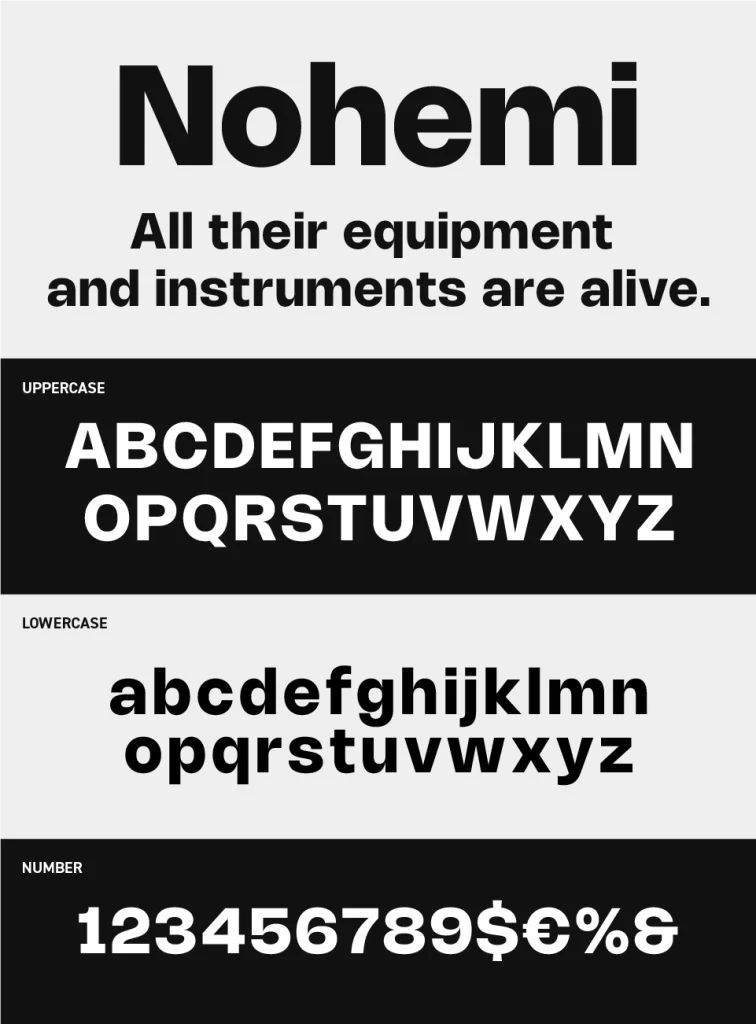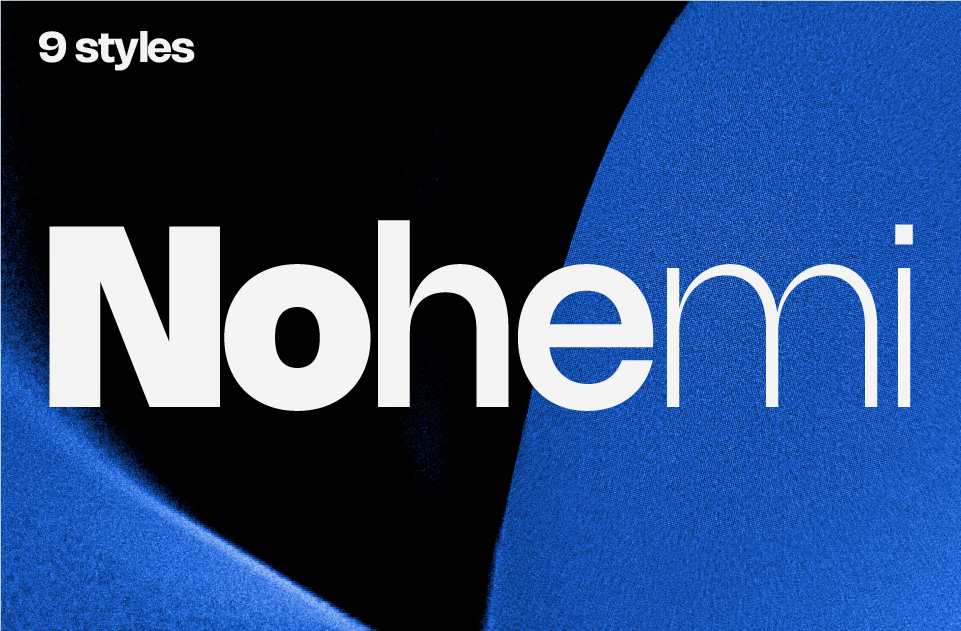
Nohemi Font
Nohemiは、丸みを抑えた幾何学的なシルエットと、均整の取れた力強いストロークが特徴のモダンサンセリフフォントです。
無駄を削ぎ落としたシンプルなデザインながら、一文字ごとのプロポーションが美しく整えられており、洗練された都会的な印象を与えます。太めのウェイトでも重たくなりすぎず、スマートさを保っているのも魅力です。
ブランディングやWebデザイン、アプリ、広告、企業ロゴなど、幅広いデザインシーンで活躍します。視認性が高く情報をすっきり整理して見せられるため、タイトルから本文まで扱いやすく、ミニマルで現代的なデザインを目指すときに頼りになるフォントです。